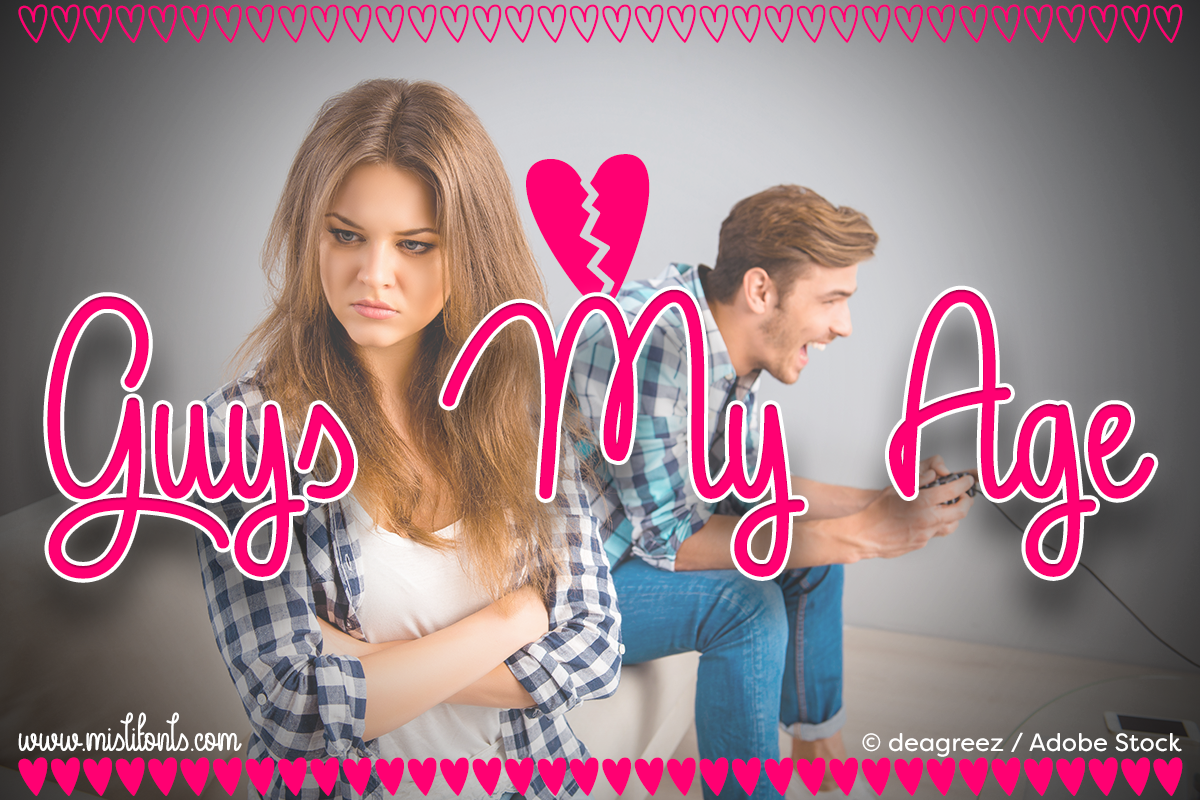
Guys My Age Font – Fonte Grátis
Guys My Age Font
Esta fonte ‘Guys My Age Font’ é perfeita para criar personalidades divertidas e animadas que combinam modernidade com um toque nostálgico. Com um design casual e acessível, ela torna-se uma escolha ótima para aplicativos de redes sociais, sites pessoais ou qualquer projeto onde você precisa de uma fonte que reflete sua individualidade. Disponível gratuitamente para uso pessoal e não comercial, é claro que a experiência completa desta fonte requer um pouco mais do seu lado. Se você estiver planejando lucrar com o uso da fonte, então será necessário adquirir uma licença de acordo com as diretrizes específicas fornecidas pelo criador Misti’s Fonts. Seja qual for o seu projeto, a ‘Guys My Age Font’ é uma opção ótima para dar vida à sua criação e torná-la ainda mais especial.